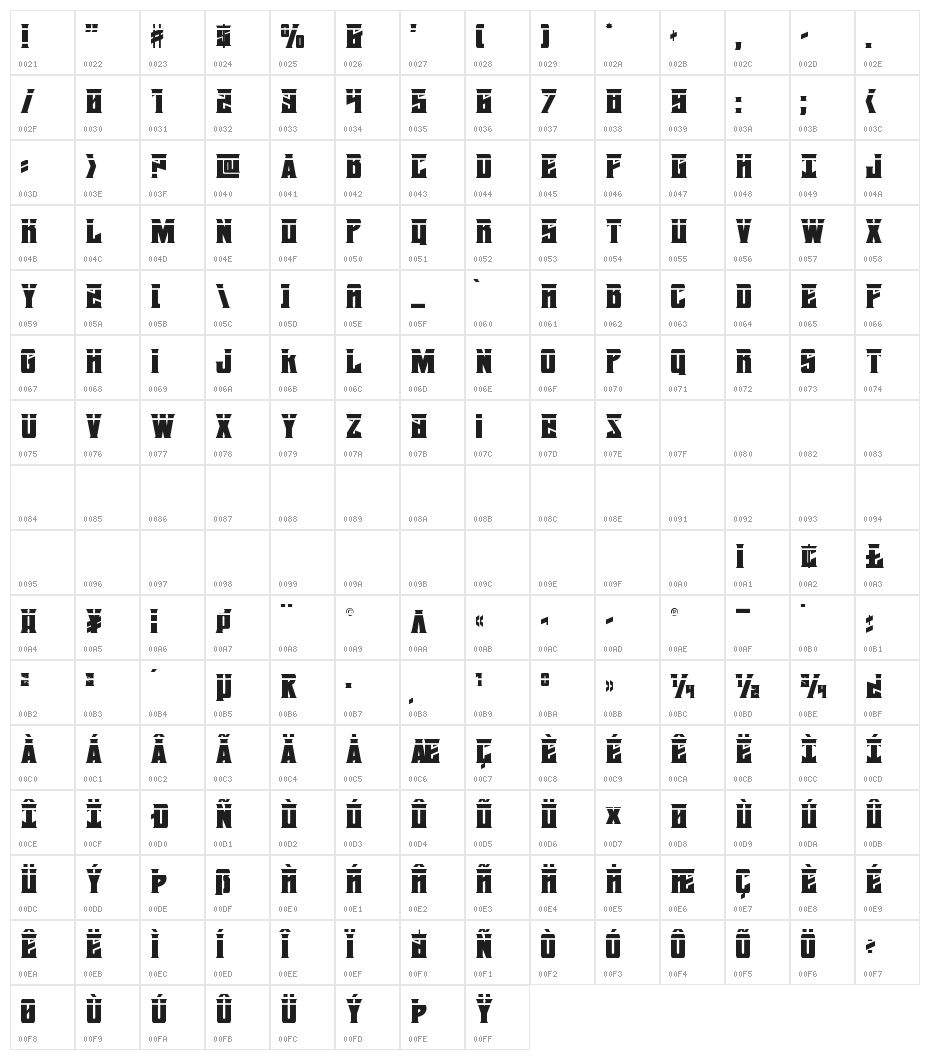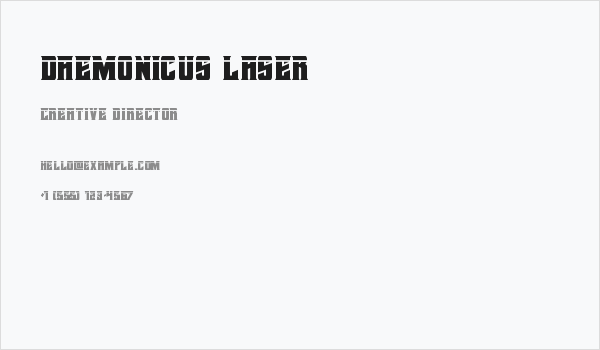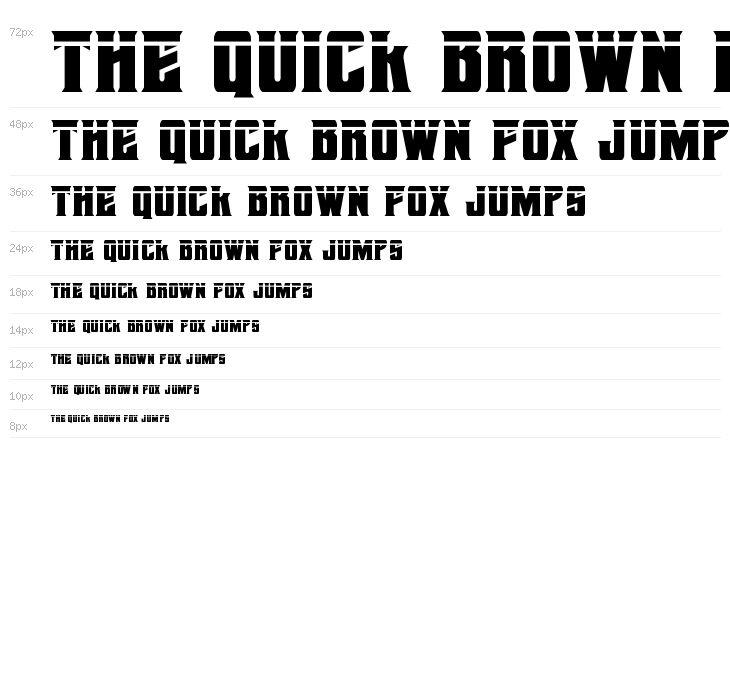
Daemonicus Laser Font
✎ Futuristic
| Gesamtstil | Futuristic, Aggressive |
| Vorgeschlagene Projekte | Ideal for sci-fi themed posters, video game titles, branding for tech companies, and any project needing a bold, futuristic look. |